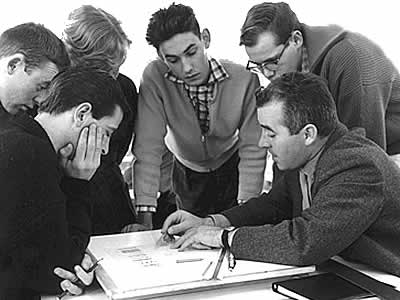
hochschule für gestaltung hfg (1953-68)As posições desenvolvidas na Escola de Design de Ulm ( Hochschule für Gestaltung, hfg) foram puristas e austeras.
A Hochschule für Gestaltung Ulm é considerada a mais significativa tentativa de estabelecer uma ligação com com os pioneiros do design alemão. Foi sucessora da Bauhaus por seus métodos de ensino, disciplinas leccionadas, ideais políticos e por também acreditar que o design tinha um importante papel social a desempenhar. Na Escola de Ulm, que prometia continuar a obra didáctica da Bauhaus, desenvolveram-se vários conceitos importantes do design do pós-guerra. Ao lado de Aicher, foram o suíço Max Bill e o italiano Tomas Maldonado que moldaram esta instituição. A Hochschule für Gestaltung Ulm foi fundada em 1953 por Inge Aicher-Scholl, Otl Aicher, Max Bill, entre outros. Procurando seguir a realidade do pós-guerra, o conceito e o programa da hgf foi uma reformulação das intenções professadas na Bauhaus. Aicher, Maldonado, Gugelot e Zeischegg, professores da nova geração, previam um design também apoiado na ciência e na tecnologia.
A Escola de Ulm desenvolveu vários projectos em parceria com a indústria, algumas de grande porte como com a empresa de electro-domésticos Braun. Os produtos projectados para a Braun ajudaram a concretizar a filosofia funcionalista da hfg. Para desenhar o cartaz do Congresso de Design de 1964, que se realizou em Ulm, Otl Aicher, um dos motores desta instituição, preferiu usar a antiquada Akzidenz Grotesk, em vez das suas sucessoras, a Helvetica ou a Univers. Alguns preferem ver no trabalho de Otl Aicher um refinado funcionalismo estrutural; contudo, o design praticado no âmbito de Ulm pecou por um rigor exagerado, aliado a uma estética pseudo-racional e estéril, desprovida de garra e de emoção, para nem falar de paixão.